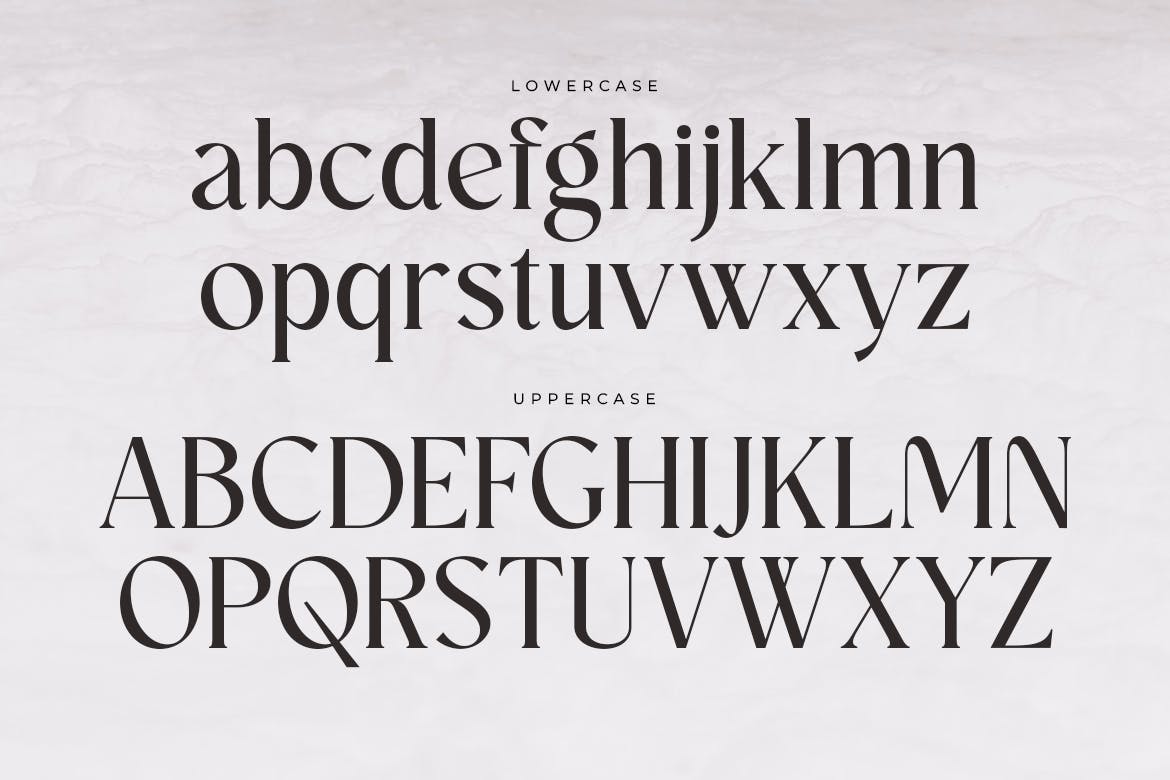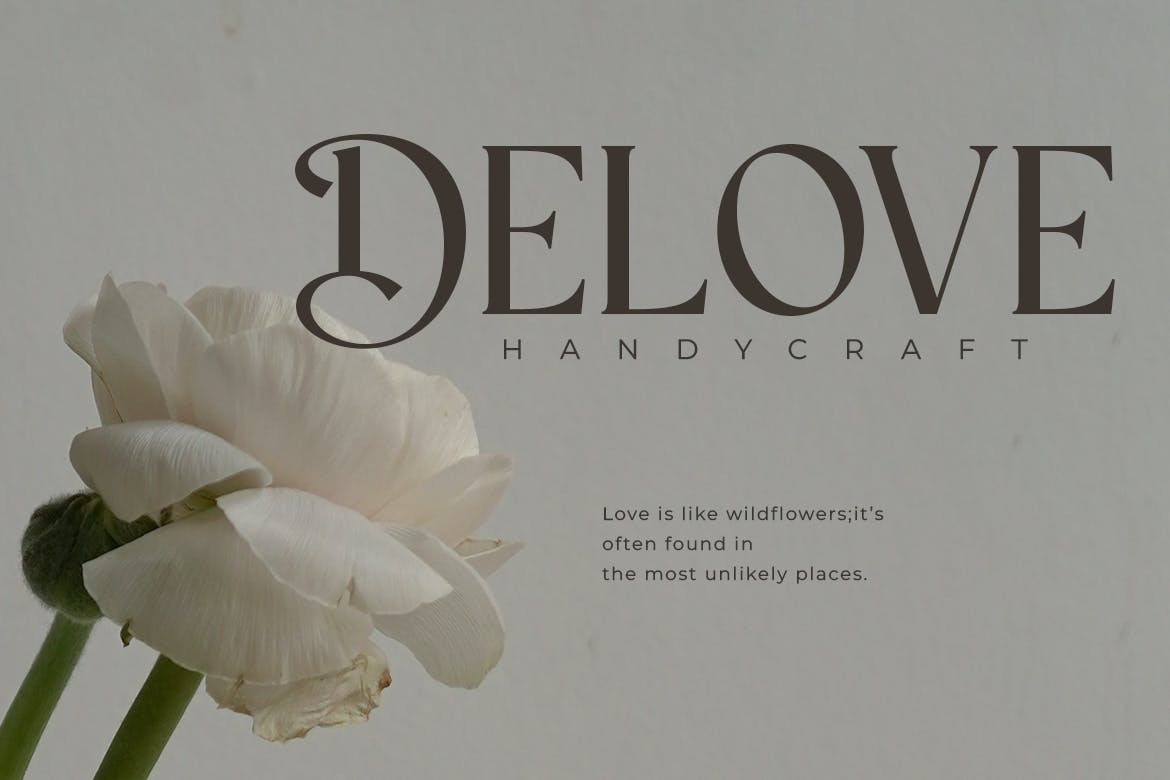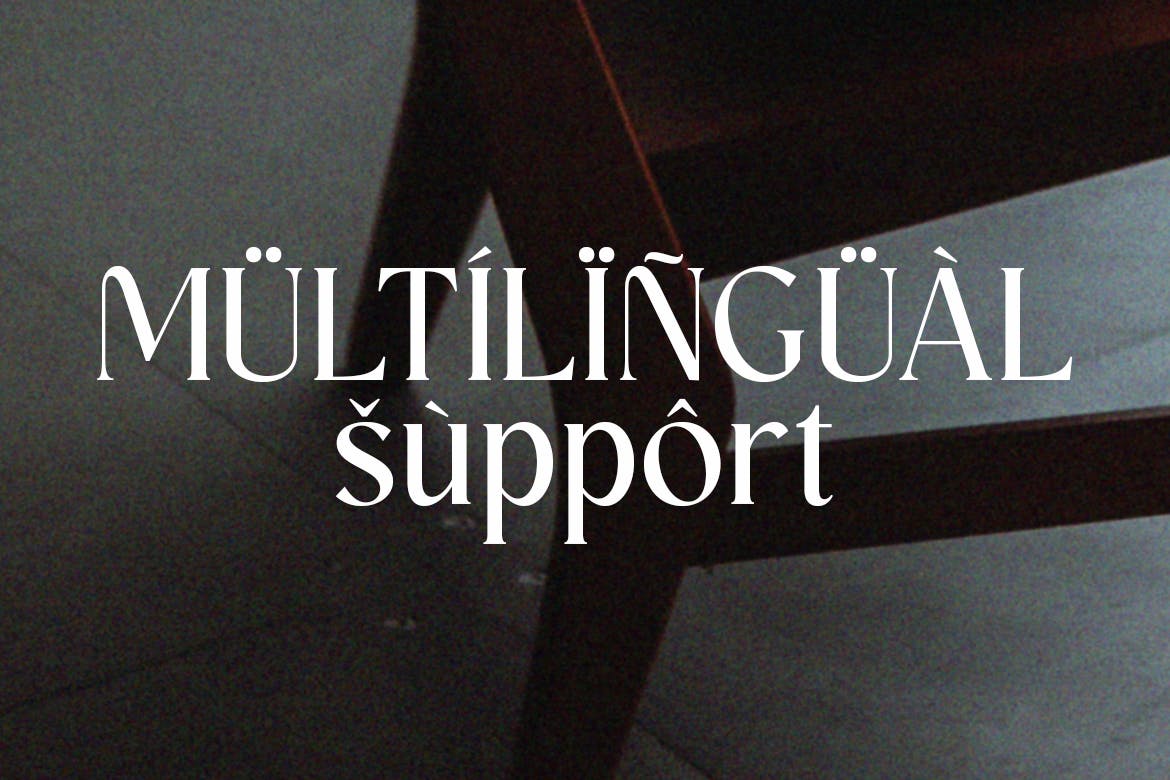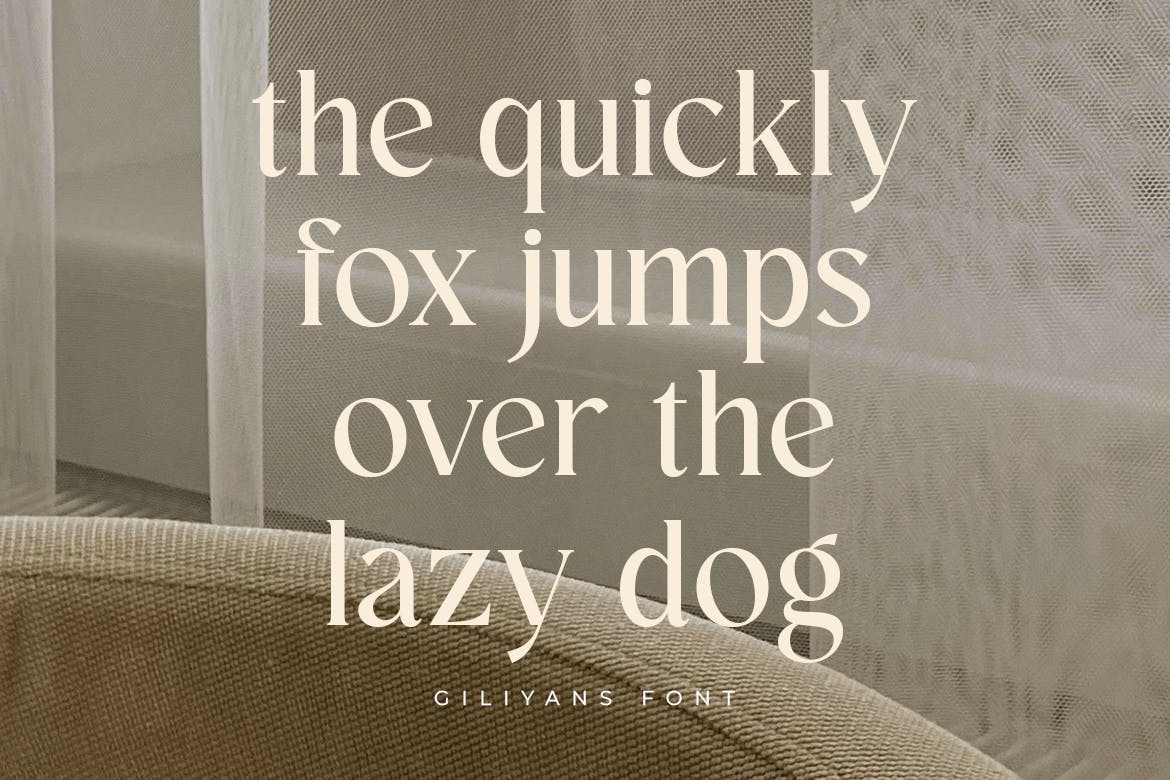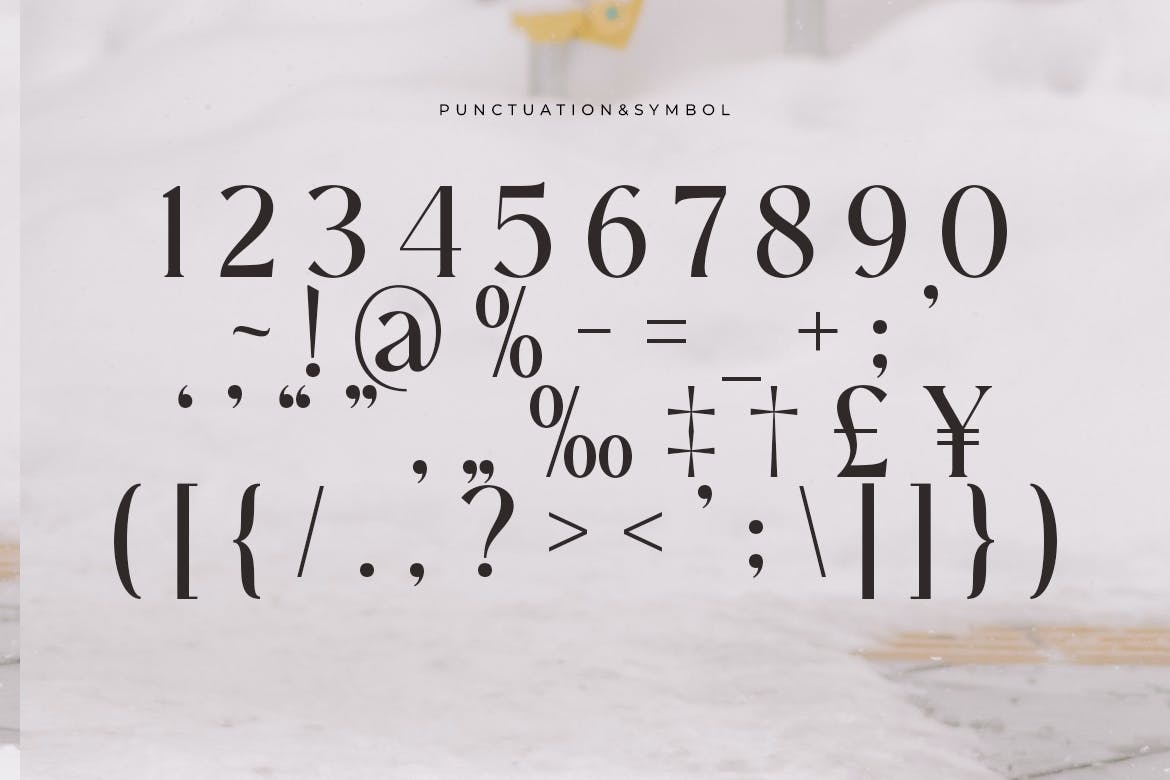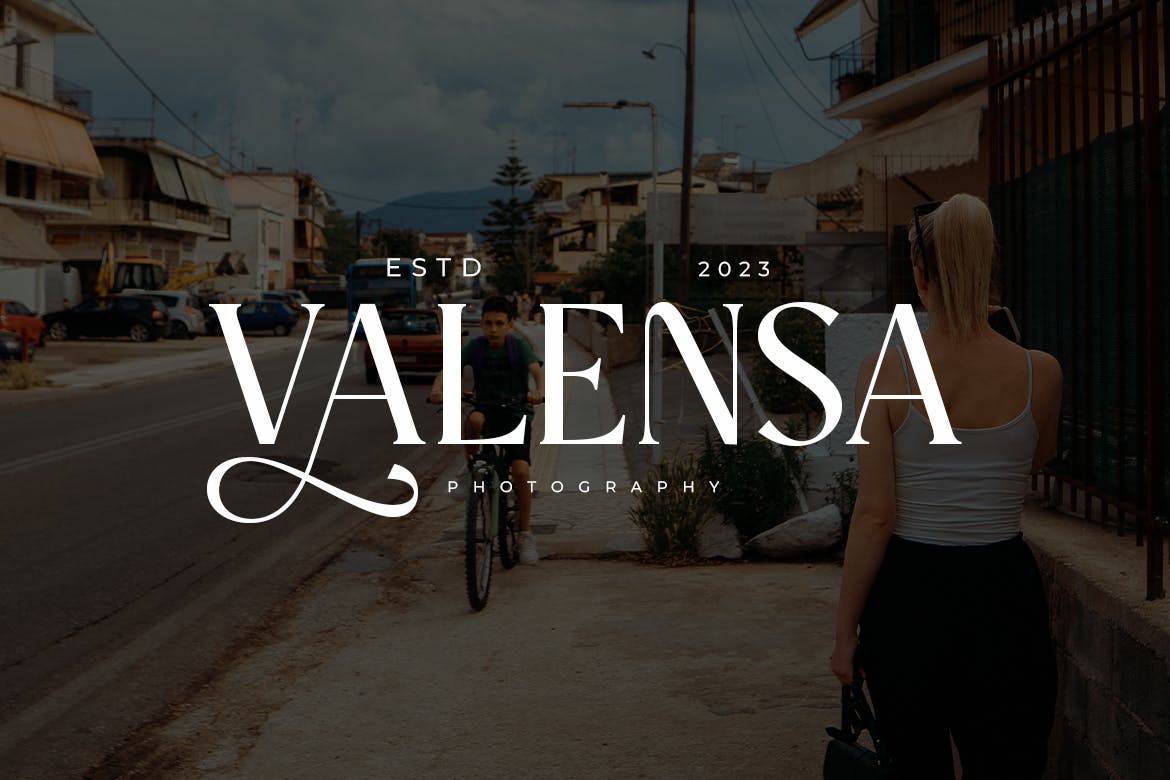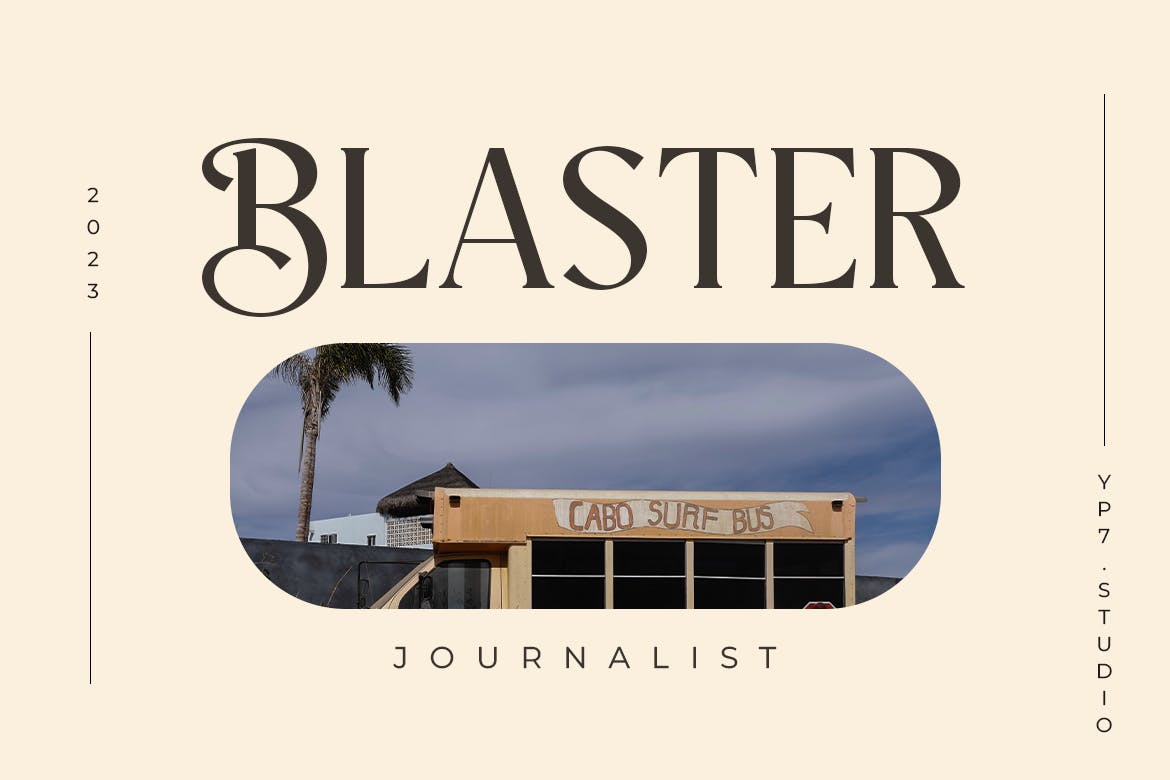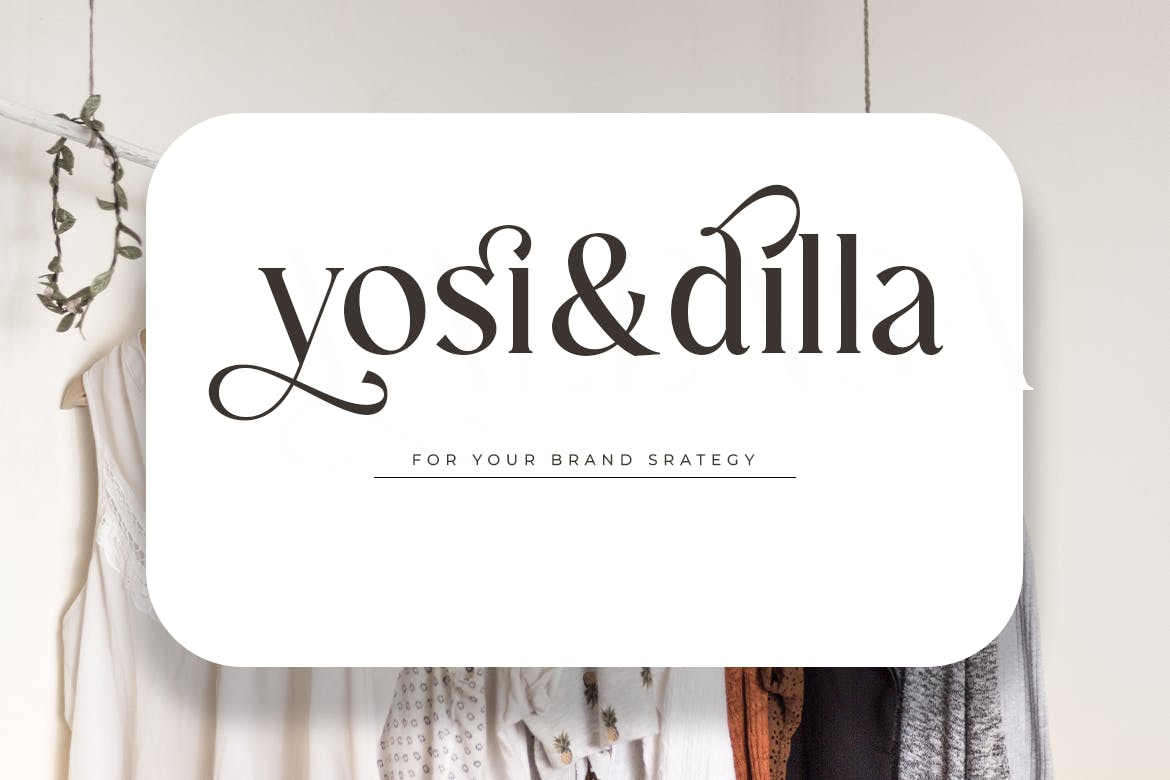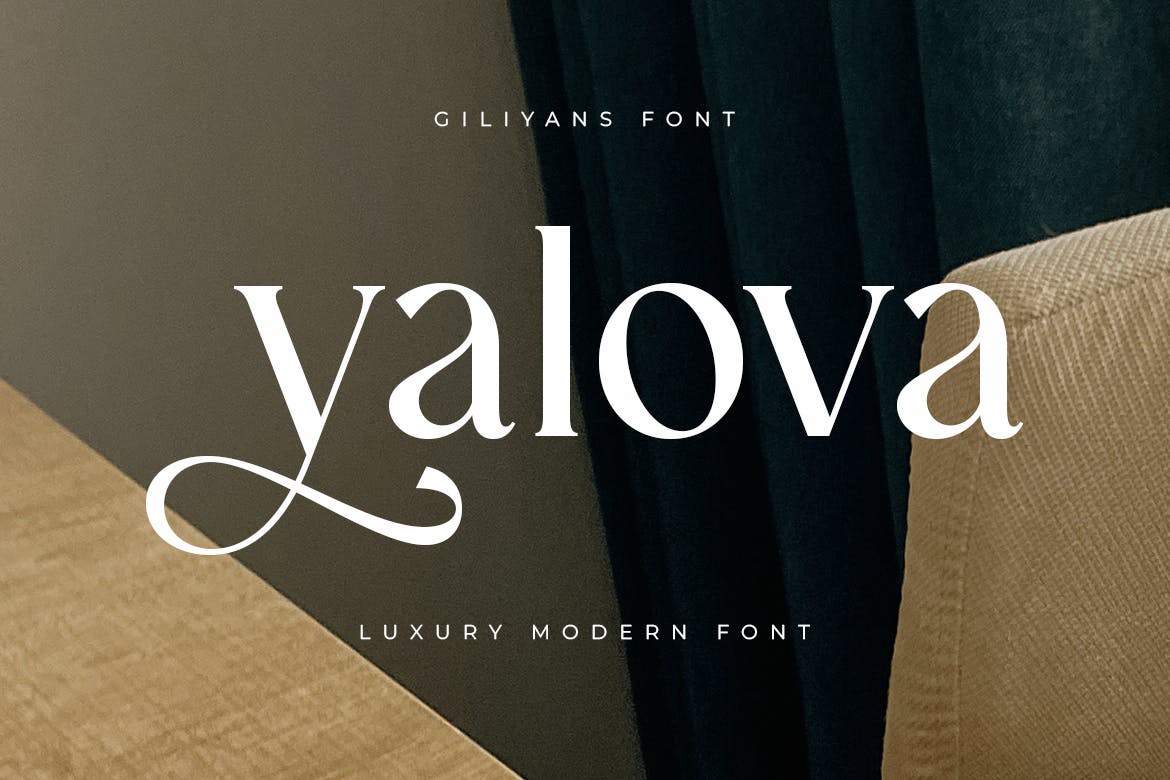
Elegant Luxury Serif Font
فونت Giliyans با طراحی شیک و لوکس، مناسب برای پروژه‌های مختلف طراحی.
فونت سریف لوکس و زیبا Giliyans
این فونت با طراحی منحصر به فرد خود، به پروژه‌های شما زیبایی خاصی می‌بخشد.